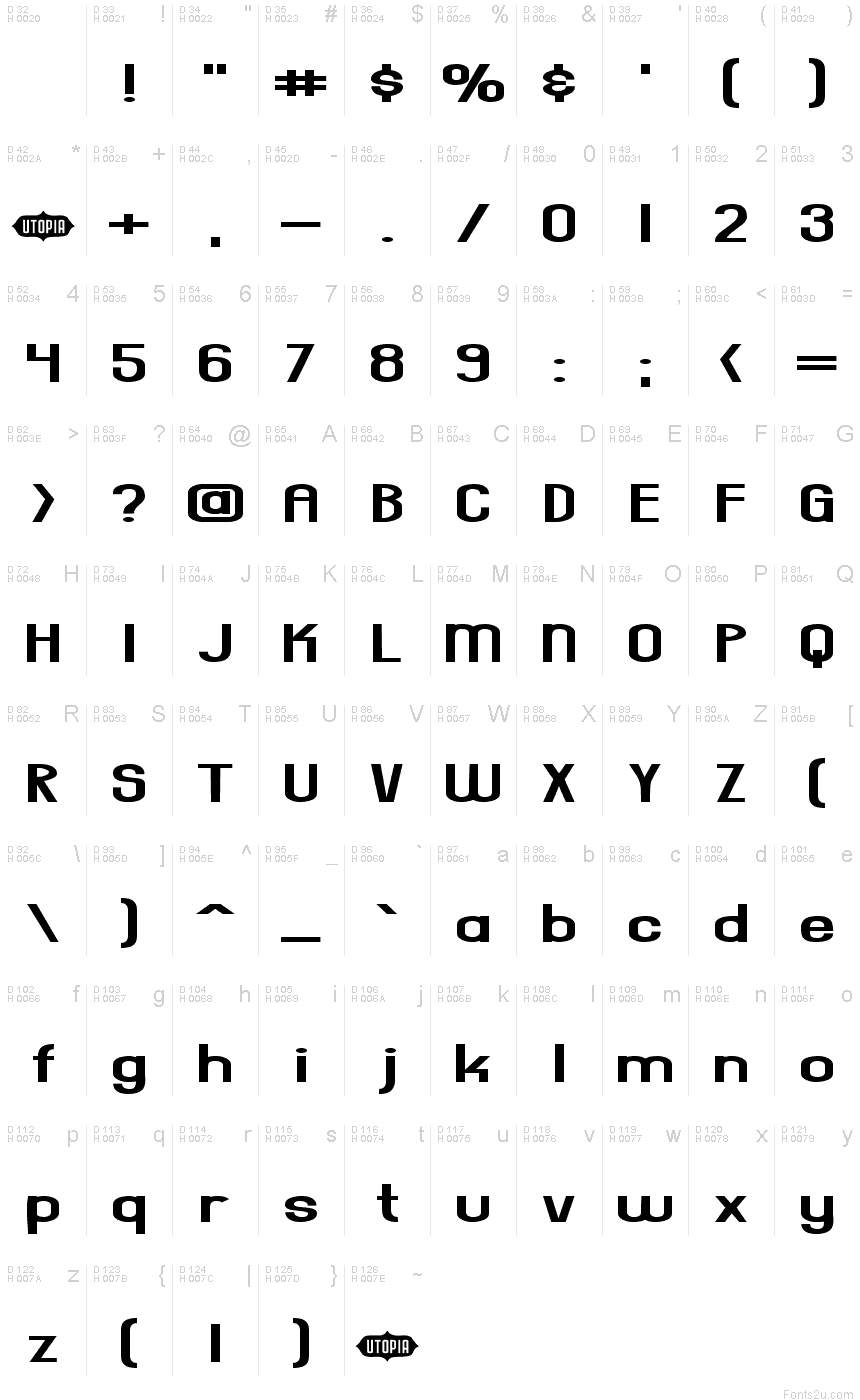
Everyday Formula
Everyday Formula od Utopiafonts to darmowy, bezszeryfowy krój pisma o solidnej, uniwersalnej budowie, który sprawia wrażenie bezpośredniego i przystępnego. Grube pociągnięcia, przestronne wnętrza znaków i wysoka x-height zapewniają czytelność nawet w małym rozmiarze, a lekko kwadratowe krzywizny nadają mu spokojnego, użytkowego charakteru. Całość wygląda na stronie wyraziście i mięsiście, przypominając ślad grubego markera, który zachowuje ostre krawędzie.
Używając Everyday Formula, możesz projektować nagłówki, elementy interfejsu, opakowania, plakaty, ziny oraz czytelne identyfikacje wizualne z zachowaniem spójnego wyrazu. Ten darmowy font sprawdza się w gęstych blokach tekstu, mając jednocześnie odpowiednią wagę, by stanowić fundament nagłówków i przycisków. Szczególnie dobrze komponuje się w parze z lekkim, geometrycznym bezszeryfem lub prostym krojem szeryfowym w dłuższych tekstach, gdzie Everyday Formula przejmuje cięższe zadania w średnich i dużych rozmiarach.